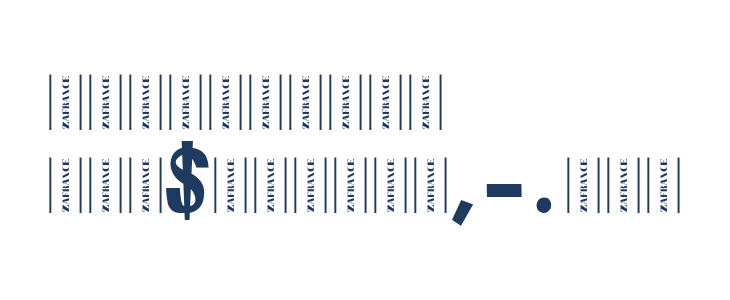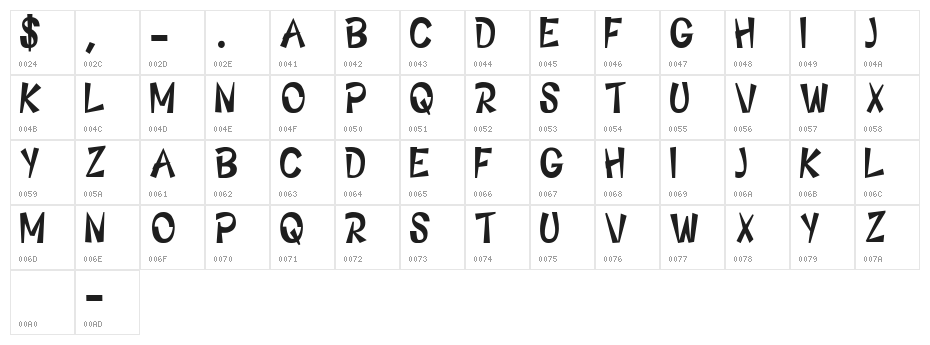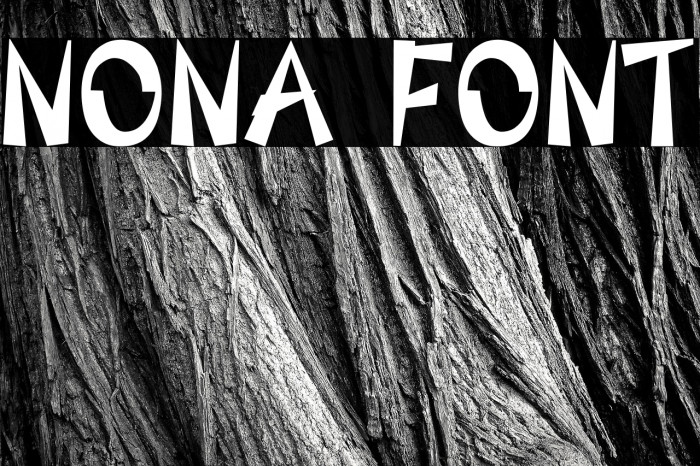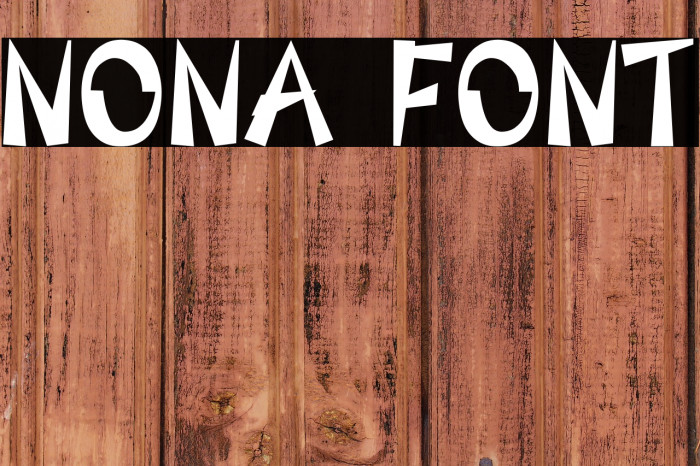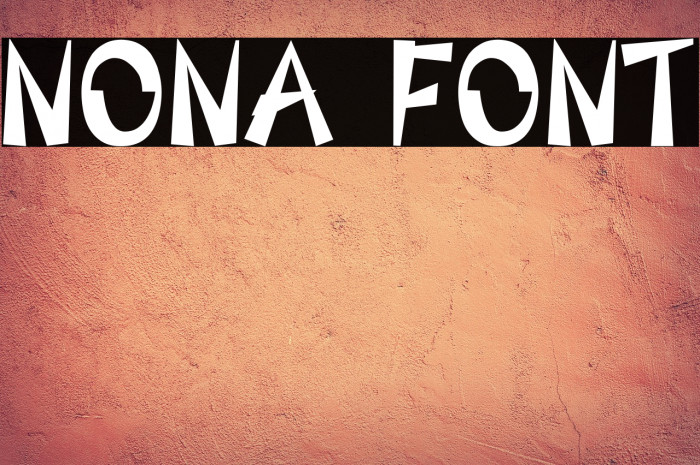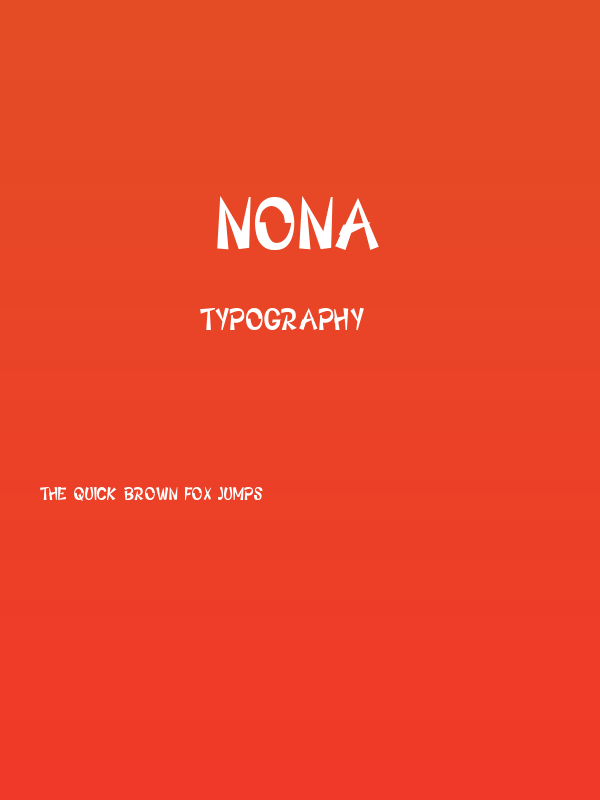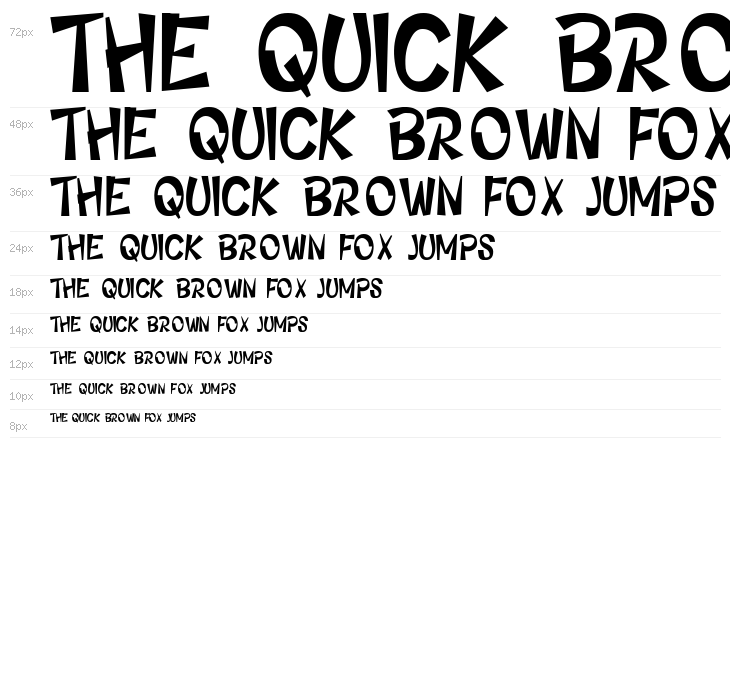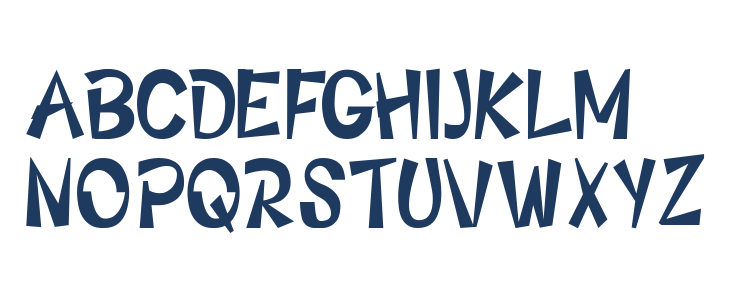
NONA Font
| Общий стиль | Playful, Energetic, Whimsical |
| Область применения | Headlines, Posters, Branding |
| Рекомендуемые проекты | Ideal for comic books, children's books, playful branding, posters, and creative advertising. |